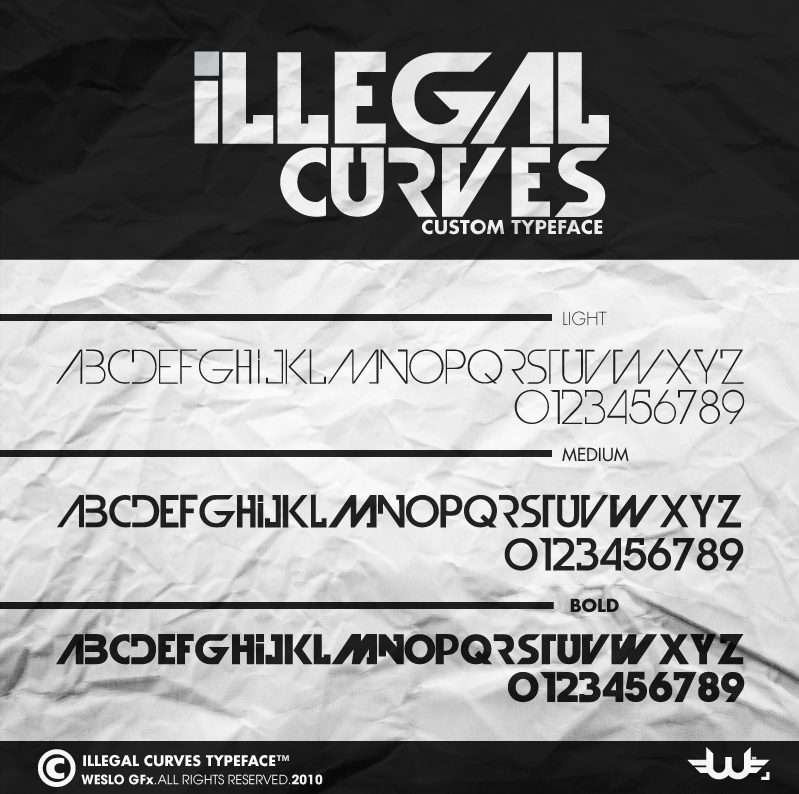
Illegal Curves Typeface – Download Grátis
Esta fonte ‘Illegal Curves’ foi criada por Wesley Pastrana Rosado (Weslo GFx), com todos os direitos reservados para o ano de 2010. Essa fonte é ideal para designers e estilistas que procuram algo único e poderoso, capaz de destacar sua marca ou projeto em qualquer cenário visual. Esse tipo de letra é perfeito para ambientes gráficos de alto impacto, como banners, logotipos ou headlines. Com uma família de caracteres completas, ela oferece opções que vão do suave e minimalista ao poderoso e vibrante, permitindo personalizar a forma da sua marca. Além disso, o designer oferece essa fonte para um pré-visualização do que ele tem criado, sem se preocupar com limitações comerciais. Quem deseja incorporá-la em seus trabalhos pode fazer uma boa contribuição e usufruir livremente dessa criação única. Ao usar o ‘Illegal Curves’, você não só adquire um recurso gráfico poderoso, mas também contribui para apoiar a criatividade deste designer talentosamente original. Esta fonte surge como uma opção para aqueles que procuram algo inovador e expressivo. Compreendemos o impacto do uso comercial desta fonte, por isso solicitamos um ‘GOOD DONATION’ ao utilizá-la; contribuindo de maneira responsável, podemos garantir que mais criadores terão a chance de compartilhar seus talentos com o mundo através da arte visual.